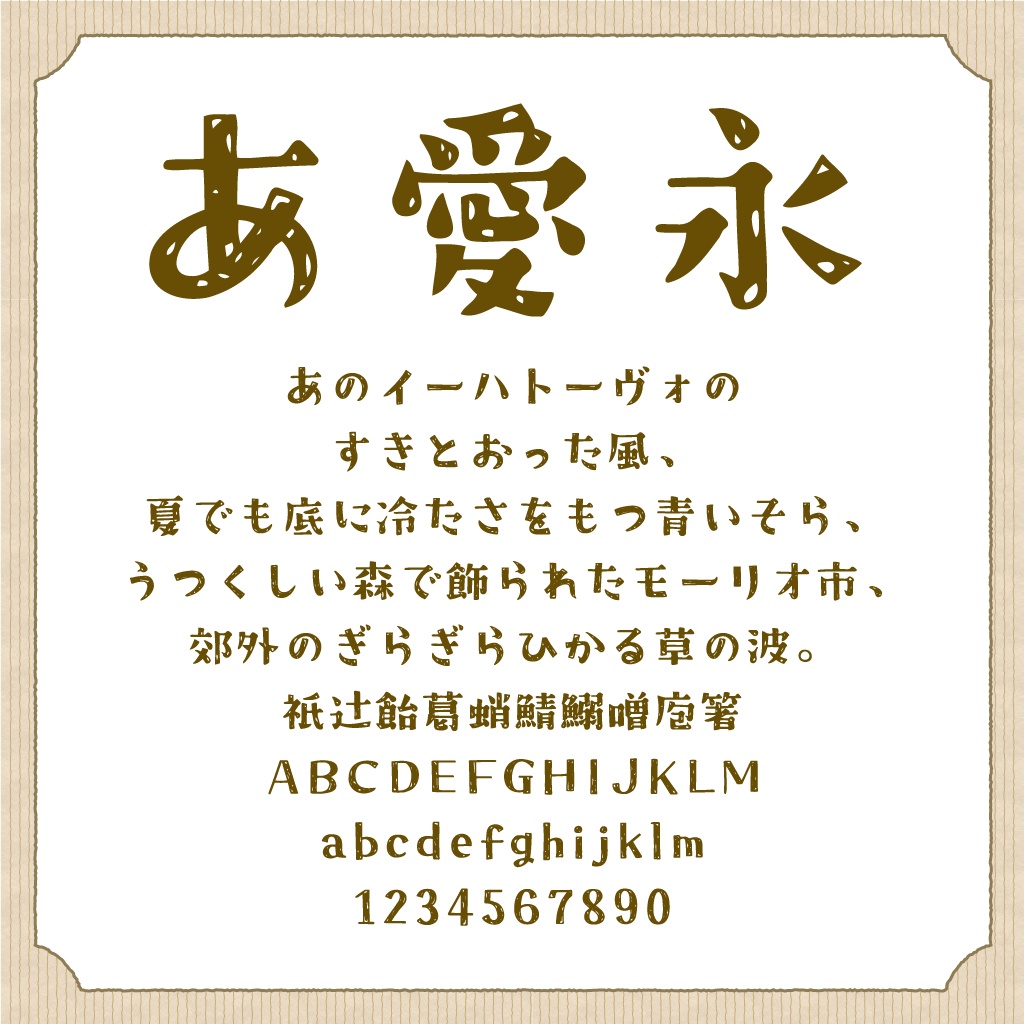
【フリーフォント】クラフト明朝
個人・商用問わず無料でご使用いただけます。 使用の際は利用規約をお読みください。 クラフト明朝は程良いかすれが特徴的な手描きの明朝体です。 投げ銭版は、ひらがな・カタカナのみの収録です。漢字は入っておりません。 収録文字 第一水準漢字(2965字)、ひらがな、カタカナ、数字、アルファベット、約物 フォントデータ形式:OpenType 印刷物・立体制作物・web・ゲーム(埋め込み可)・映像・LINEスタンプ・電子書籍などにお使いいただけます。 禁止事項 ・公序良俗に反する目的、誹謗・中傷目的での利用。 ・フォントファイルのみの再配布・販売。 フリーフォントですが、著作権は放棄しておりません。 フォントの使用により発生したと思われるいかなる損害についても責任を負いません。 本ファイルは武蔵システム(http://opentype.jp/)の(OTEdit for Mac)を使い作成しました。